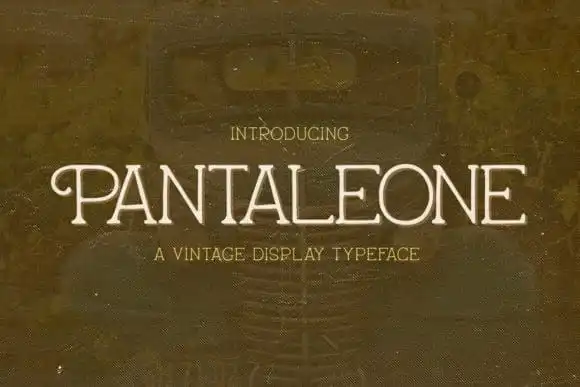
Pantaleone Serif Font – Download Grátis
A Pantaleone Serif Font é uma tipografia inspirada em sinais de metal vintage. Desenhada pela Rillatype e compartilhada no site 99designs, essa font se destaca por tornar a criação de designs vintage mais agradável e conveniente. Suas linhas sólidas e elegantes permitem que você crie um design com profundidade e personalidade para seus projetos de embalagens, marcas, citações ou qualquer aplicação em que desejar adicionar um ar nostálgico. A Pantaleone é perfeita tanto para quem busca manter o espírito antigo em suas criações quanto para designers que desejam dar um toque vintage a seus trabalhos digitais. Seja você criando novas marcas, revivendo uma identidade visual ou apenas adicionando um toque de sofisticação a sua próxima design de marca – essa fonte é certamente uma escolha inteligente.